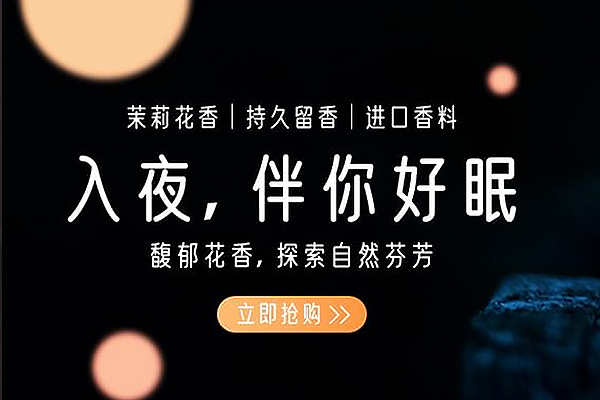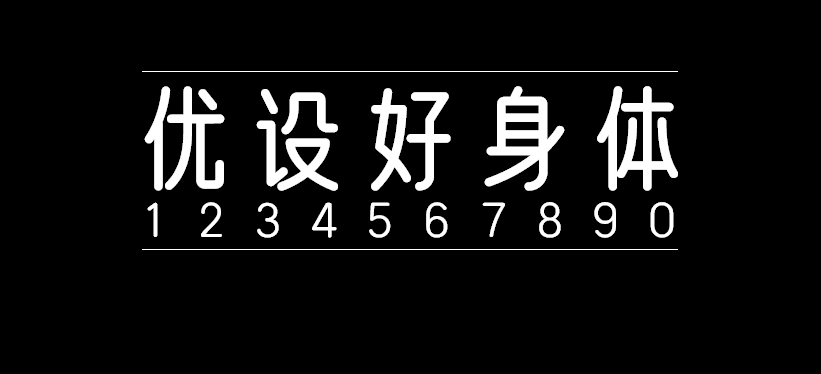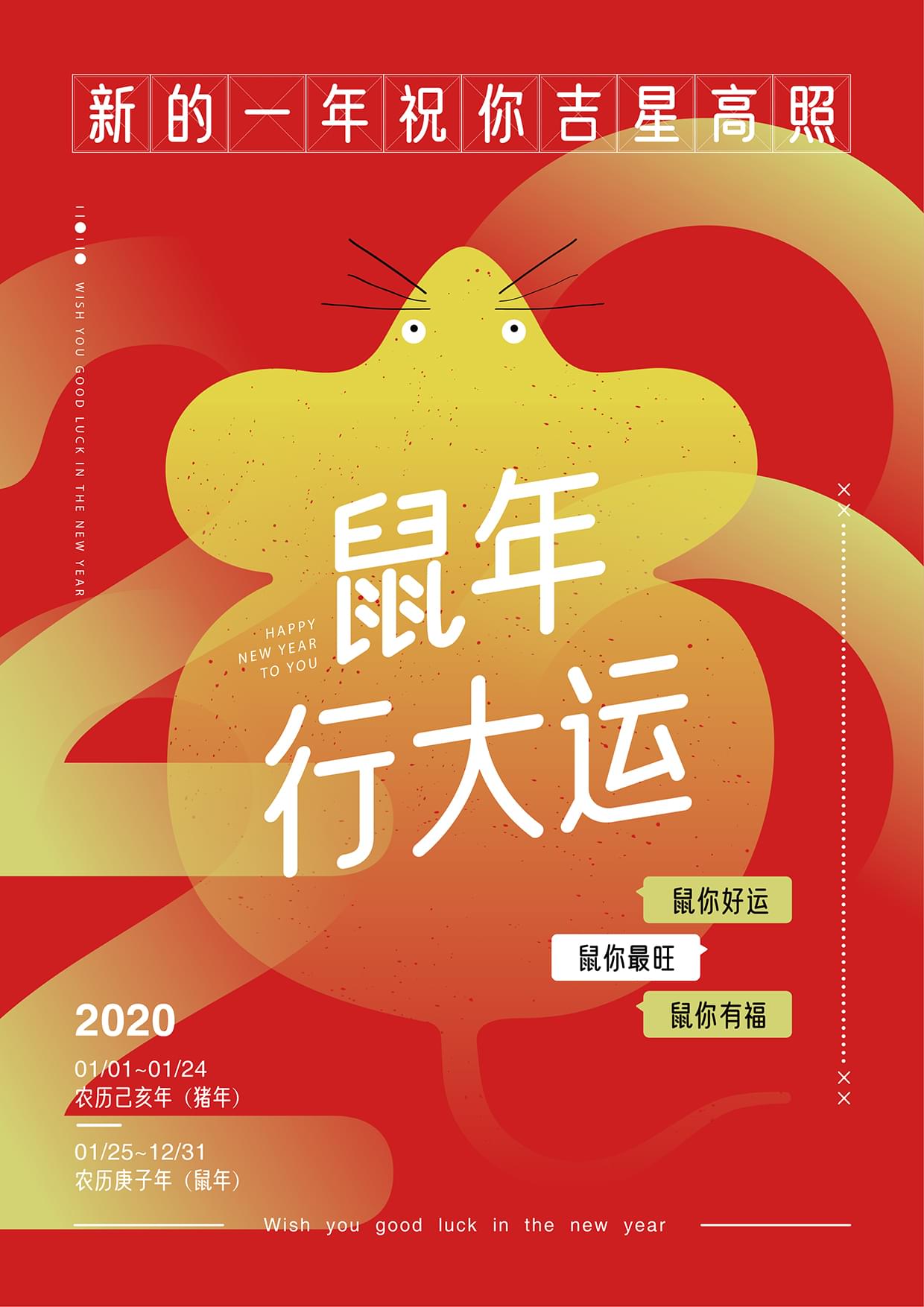
优设好身体
优设好身体是一款亲和力、现代感极强的专业美术标题字体。它以圆体字型为基础,通过瘦高的字面、偏向几何的曲线,让整宽字体富有亲和力和时尚感。在同样的面积里,更窄的字面就意味着能容纳更多的信息,所以这款字体非常适用在需要体现亲和力与时尚感的各类品牌宣传广告和产品包装设计的标题上。
这款字体的命名和风格去年 10 月份就定下来了。 优设初衷是希望设计师们用了这款字体,能减少改稿的次数,少点熬夜有个好身体。现在遇上疫情,更是成为我们对每个人的祝福,希望大家都像这款字体名字一样,平平安安有个好身体!